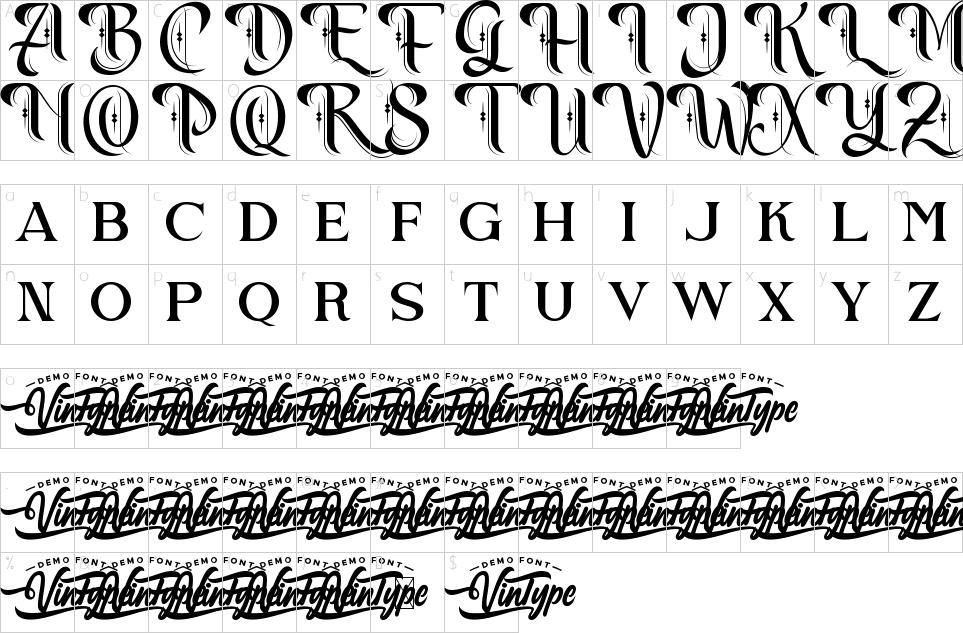
Angel Bandit Font – Fonte Grátis
Angel Bandit Font
A fonte ‘Angel Bandit Font’ é um charmoso e moderno recurso gráfico que oferece um toque de personalidade para os projetos digitais. Especialmente adequada para o estilo gráfico, o design da font foi criado pela VinType e já foi baixada mais de 10.867 vezes. Seja para criar logotipos, designs de ícones ou até mesmo para incorporar em seu site, esta font é um excelente complemento. Com suas linhas atraentes e elegantes, ‘Angel Bandit Font’ proporciona uma textura única que enriquece qualquer projeto visual, tornando-o ainda mais atraente e memorável. Engane-se em não perceber que, uma vez adicionada à sua biblioteca de fontes, esta font se tornará uma das favoritas, já que suas características sofisticadas e personalizáveis irão transformar a forma como você cria.